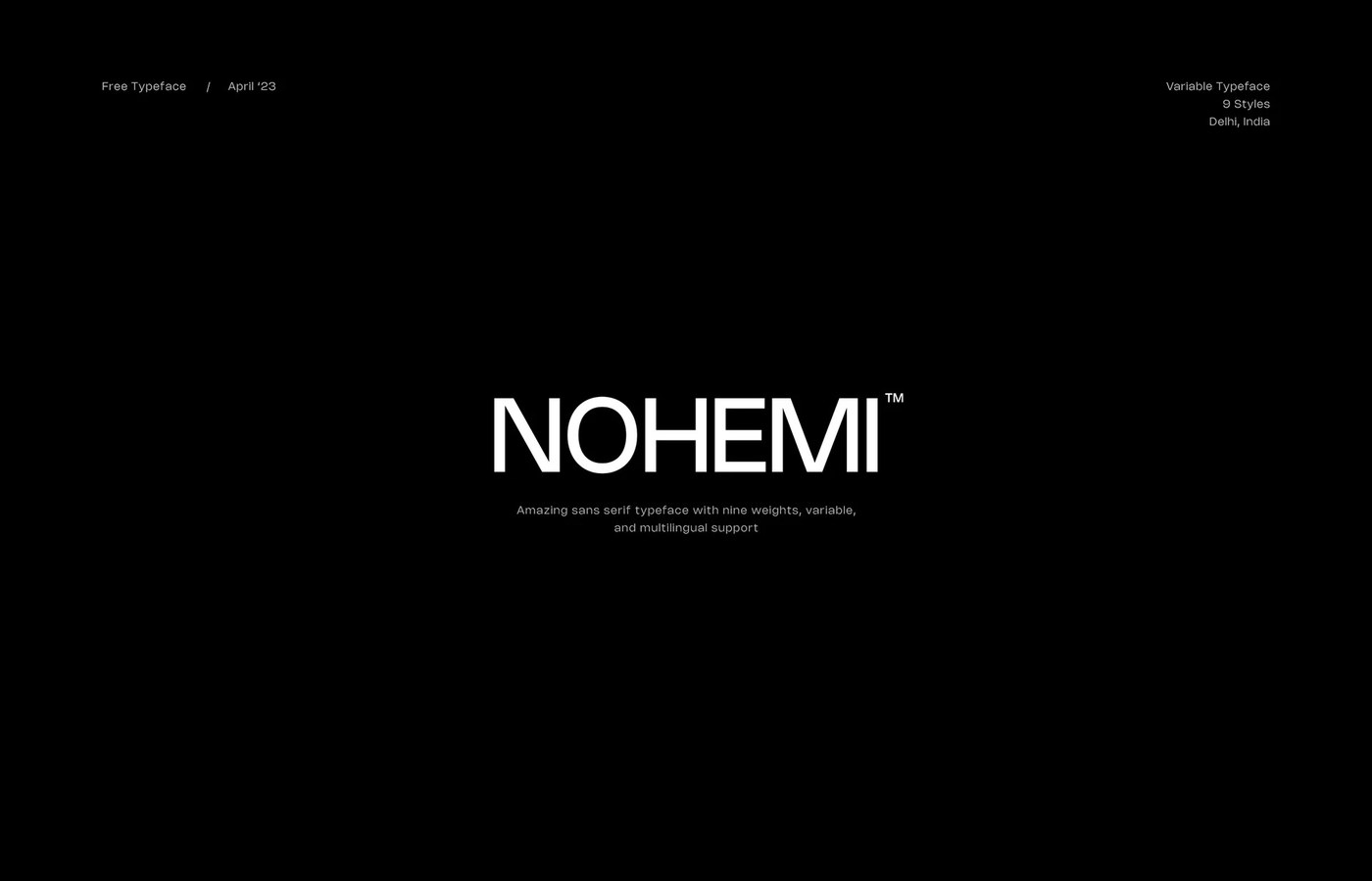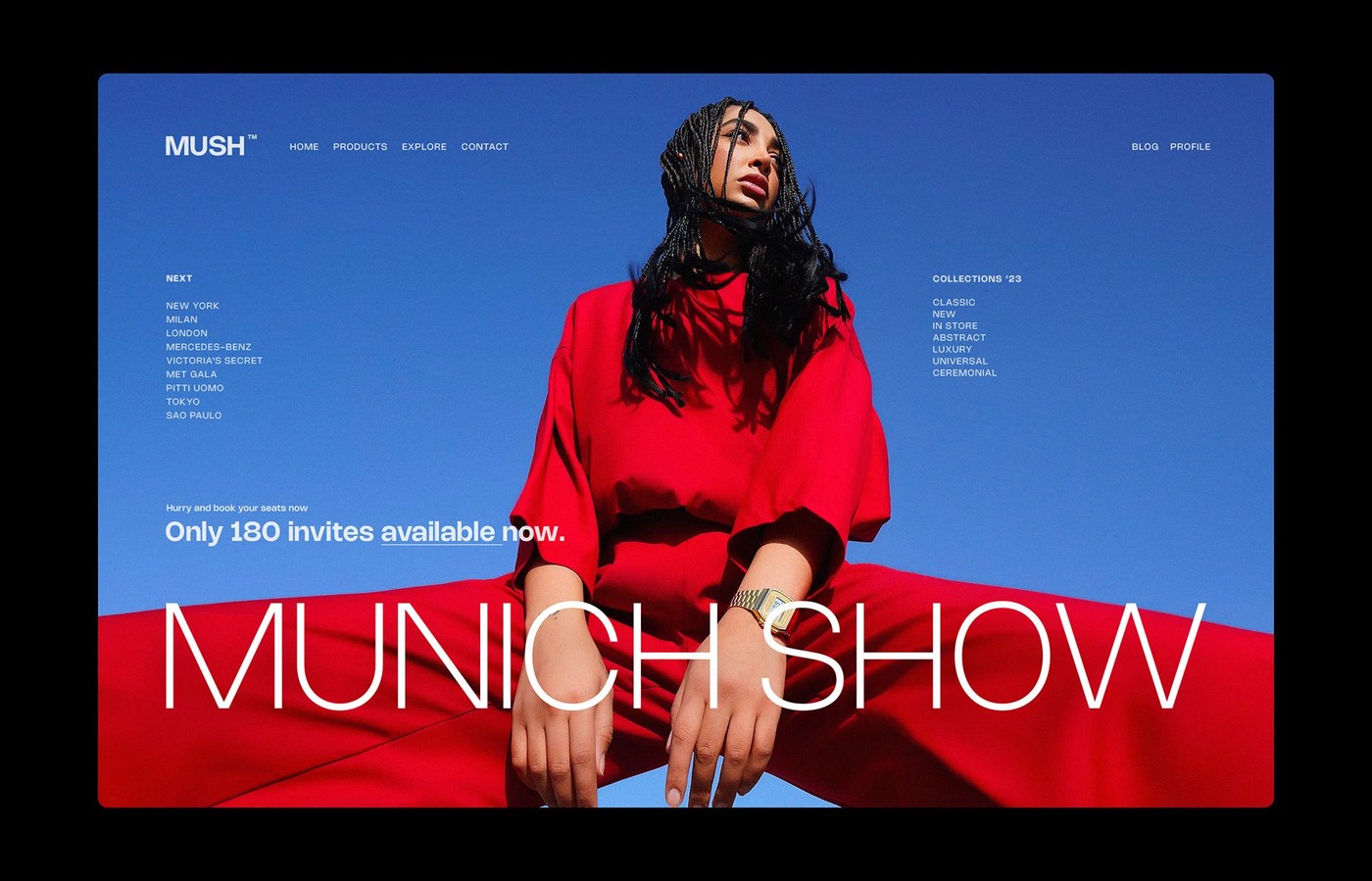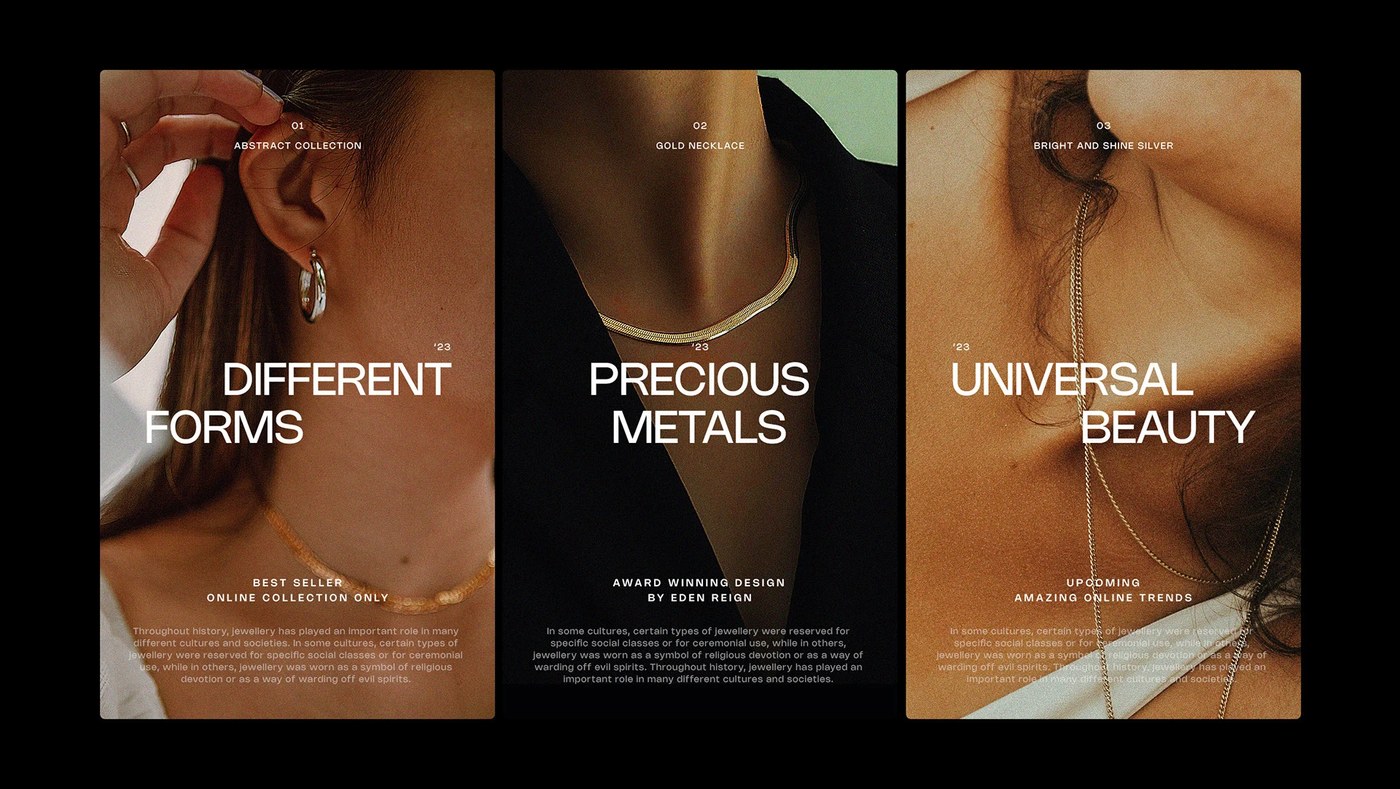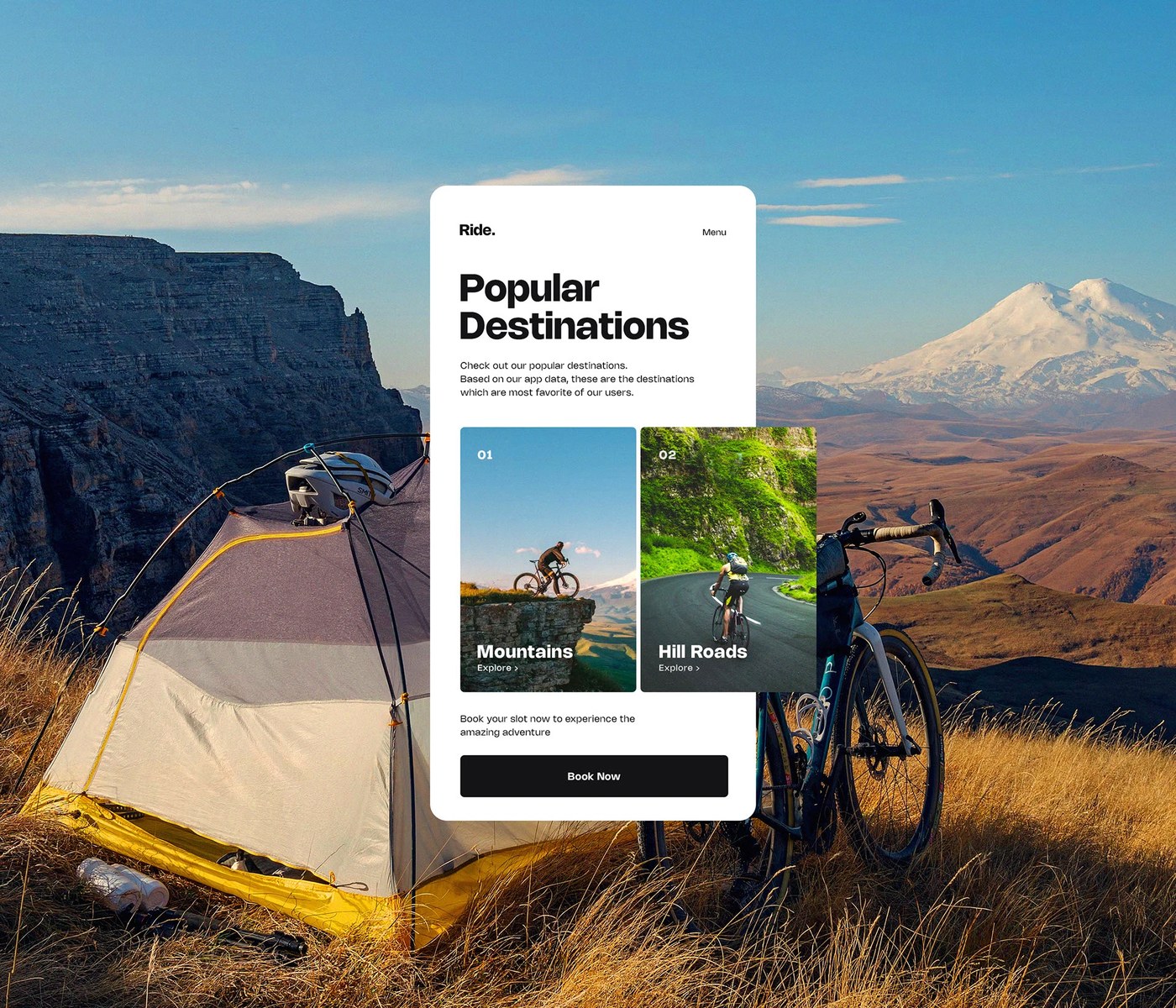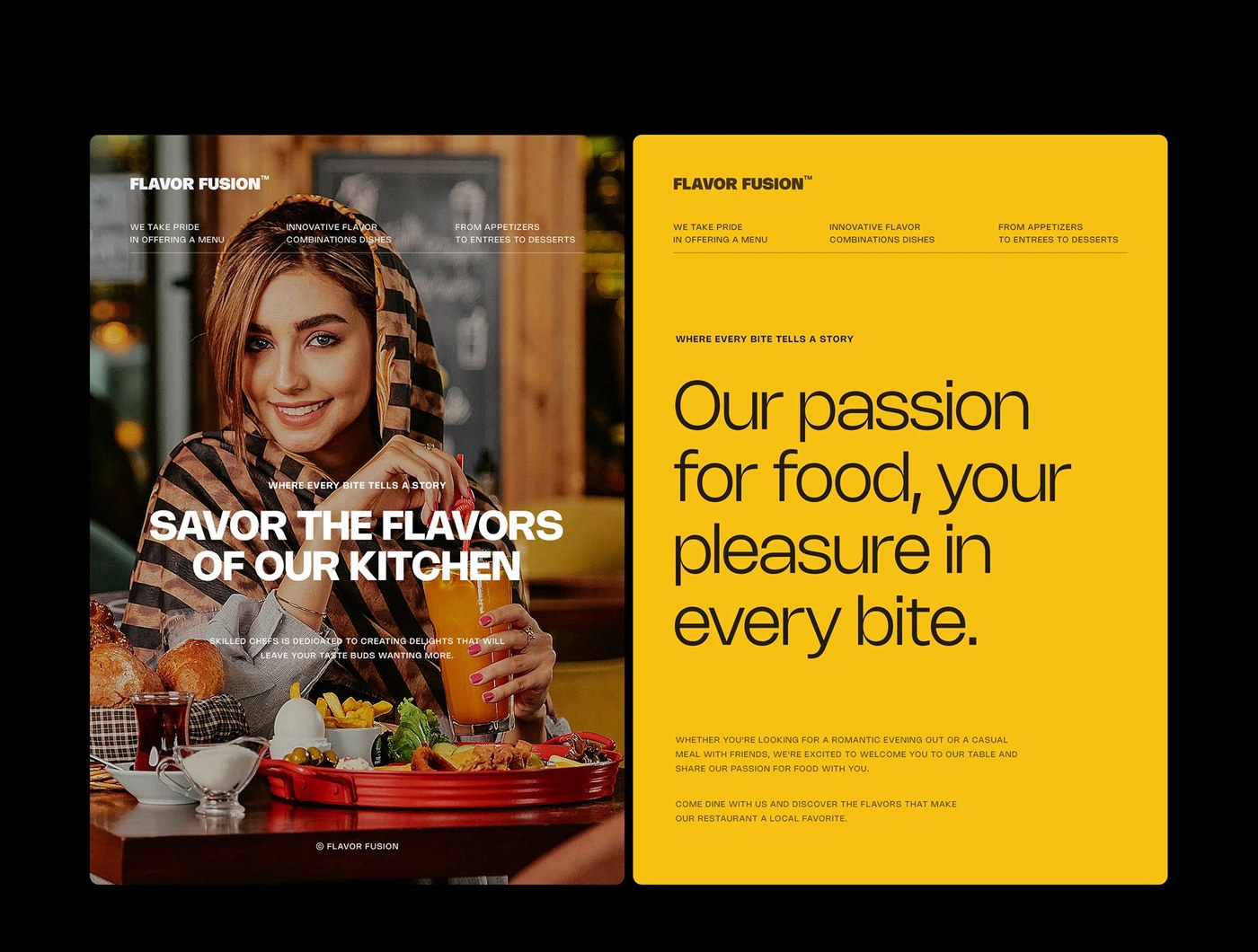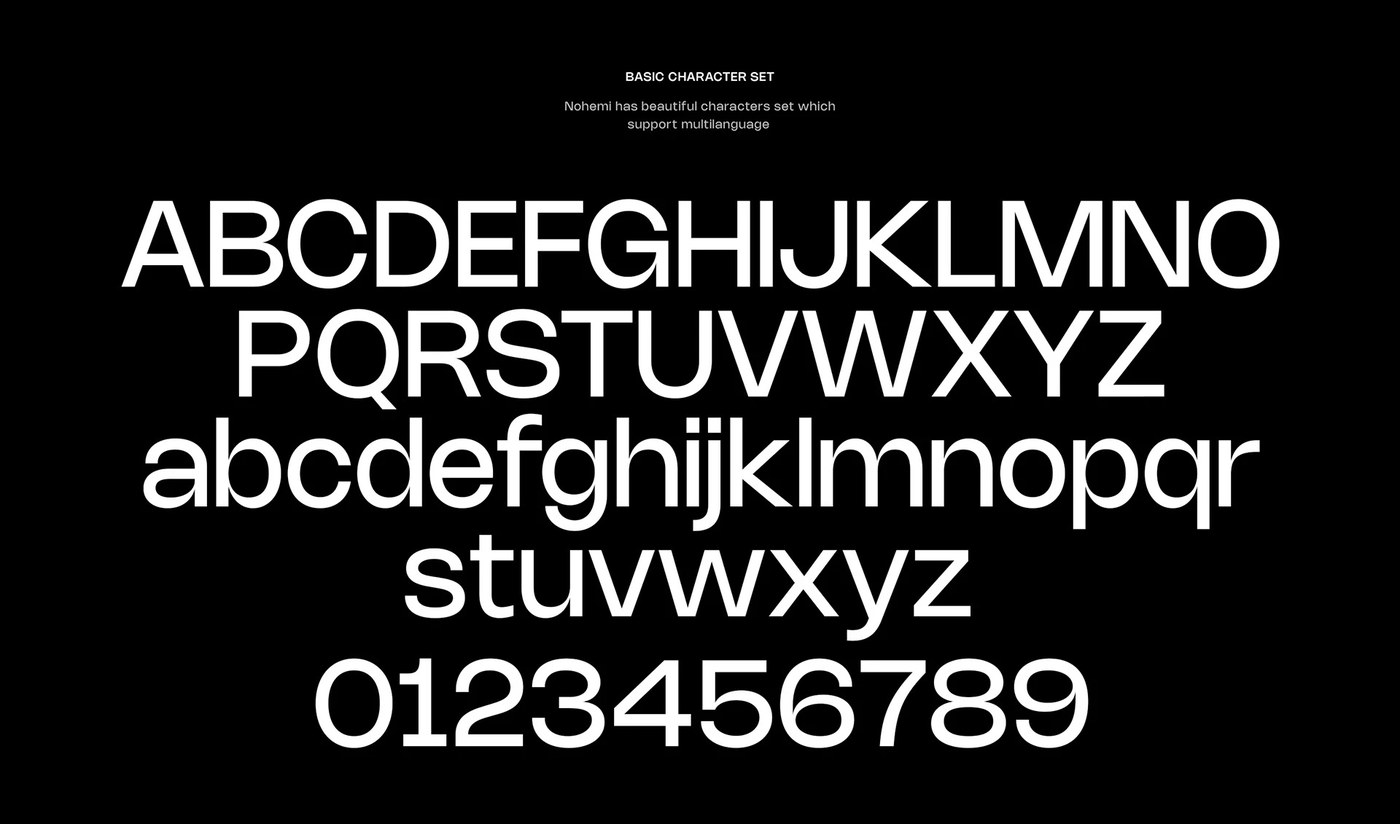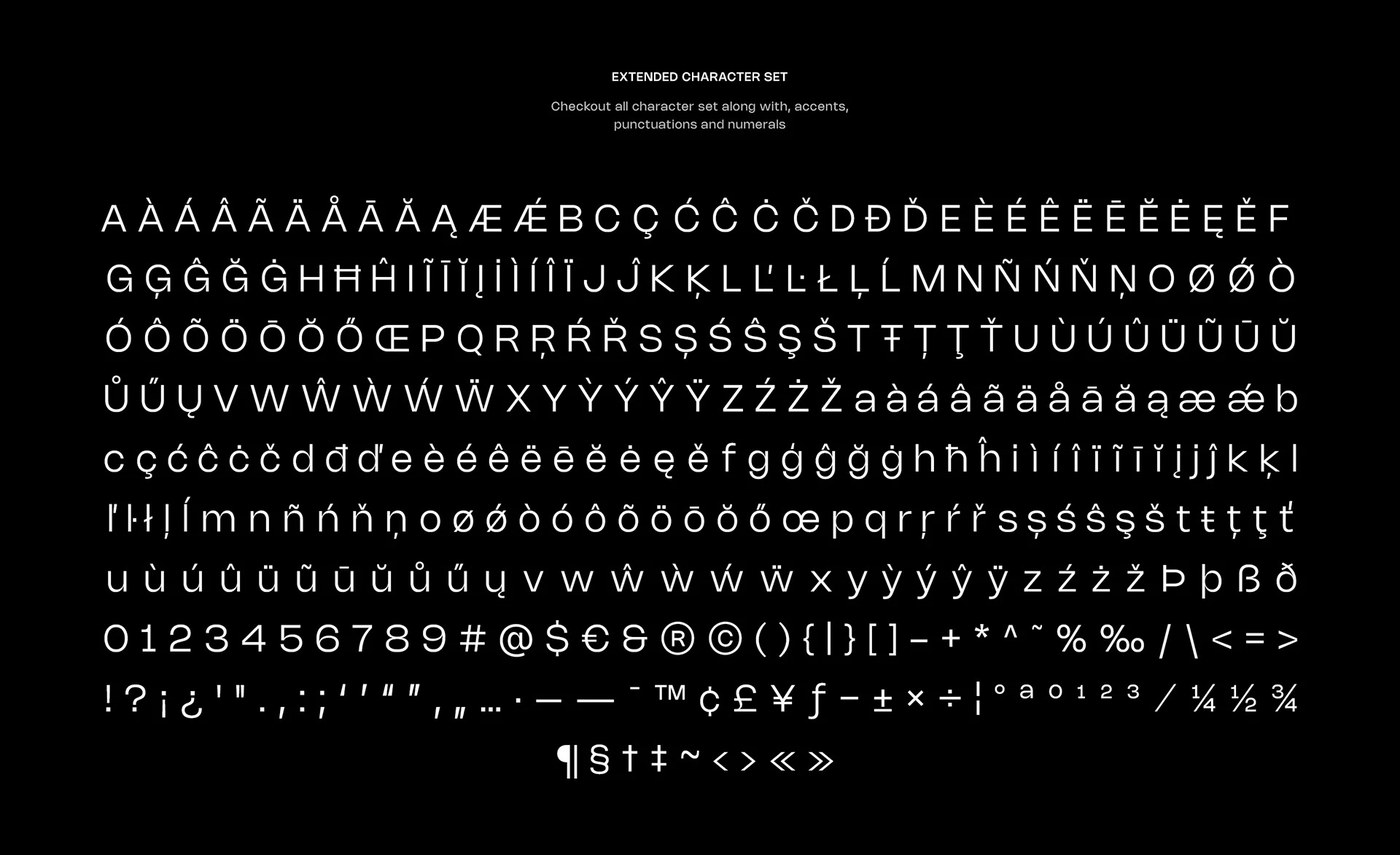
Nohemi là một display typeface variable font mới toanh của Rajesh Rajput. Thiết kế này mang phong cách Swiss cực kỳ sạch sẽ và sự kiểm soát hình học đỉnh cao cho các layout hiện đại.
Các chữ cái (letterforms) của font này được xây dựng dựa trên hệ lưới (modular grids). Những khoảng trắng âm lớn (large negative spaces) tạo ra một nhịp điệu thị giác sắc nét. Mọi đường viền đều căn thẳng tắp. Các chi tiết kỹ thuật giúp tạo ra độ tương phản xúc giác mạnh mẽ. Chính sự kỷ luật này cho phép typography trở thành tâm điểm chú ý. Thiết kế tránh các đường trang trí thừa thãi, chỉ sử dụng các đường cong hình học phẳng. Các quy tắc spacing sạch sẽ giúp cân bằng bố cục. Designer có thể tổ chức các thông tin phức tạp một cách dễ dàng. Hệ lưới sẽ dẫn dắt mắt người xem xuyên qua trang giấy. Cấu trúc contrast cao đảm bảo tính dễ đọc (readability). Mỗi glyph đều có kích thước chính xác. Khoảng cách (spacing) luôn nhất quán dù thay đổi kích cỡ. Các hình khối trông rất chắc chắn và có cấu trúc. Sự trật tự thị giác này giúp neo giữ toàn bộ layout. Nó tạo ra một cấu trúc siêu vững chãi cho các headline.
Thiết kế một Hệ thống Font Variable Display Typeface Đồng bộ
Tính năng variable axis có tới chín mức độ nặng nhẹ (weights) khác nhau. Bộ ký tự (character set) tự điều chỉnh mượt mà. Nó hoạt động tốt dù là cho các header cỡ lớn hay các caption nhỏ xíu. Các weight nhẹ (light weights) mang lại cảm giác sạch và thoáng. Còn các weight nặng (heavy weights) thì lại toát lên sự uy lực kiến trúc mạnh mẽ. Một nền màu cam-đỏ đậm (saturated orange-red field) tương phản với chữ trắng sắc nét. Designer có thể dùng font variable display này cho cả poster vật lý. Nó cũng cực kỳ “ăn khớp” với các ứng dụng digital. Sự chuyển đổi giữa các style cực kỳ mượt mà. Font vẫn giữ được độ dễ đọc cao trên màn hình di động (mobile screens). Các điều chỉnh contrast giúp bảo vệ khoảng không gian bên trong của mỗi chữ. Family font này là một giải pháp scaling typography tuyệt vời. Nó đáp ứng tất cả các nhu cầu truyền thông hiện đại.
Rajesh Rajput tạo ra những công cụ siêu tinh tế. Font này cập nhật các lý tưởng hiện đại chủ nghĩa Swiss cổ điển. Nó được thiết kế cho layout màn hình vào năm 2026. Font display variable này đứng vững như một món đồ vô cùng linh hoạt trong bộ công cụ của bất kỳ designer nào. Nó còn là tài liệu tham khảo hoàn hảo cho các kiến trúc sư identity. Các designer hiện đại có thể kết hợp những glyph (glyph) cô đọng này với các font grotesque rộng hơn. Sự kết hợp này tạo ra một hệ thống phân cấp (hierarchy) rất sang trọng. Family này hợp với các sản phẩm bán lẻ (retail specimens) và thiết kế editorial. Nó đại diện cho một giọng điệu thiết kế vượt thời gian.